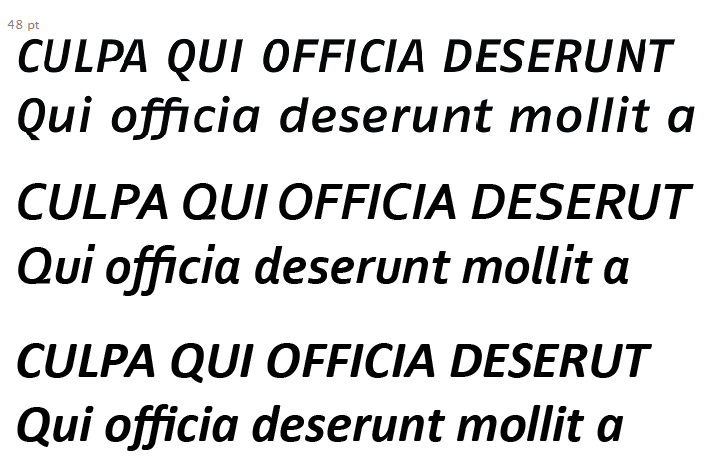
Schrift ähnlich FF Fago Pro Extended Medium Italic gesucht
kann mir jemand einen Tip geben, ob und wo es eine kostenlose Schriftart gibt, die so ähnlich aussieht wie FF Fago Pro Extended Medium Italic?
auf dem bild zu sehen
Fago extended medium italic
Corbel italic
Calibri bold italic